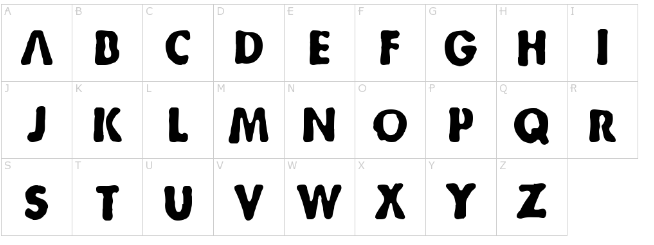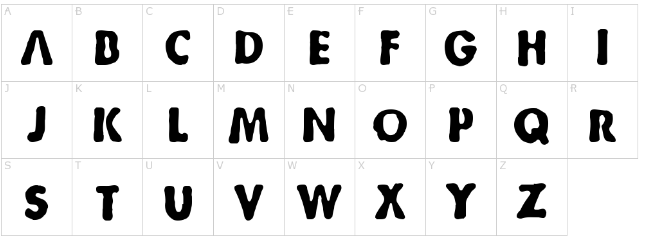
Bộ Font: Font Bootleg
Phân loại: Cá tính
Font Bootleg là một kiểu chữ độc đáo mang đậm phong cách cổ điển và retro, thường được sử dụng trong các thiết kế cần sự phá cách và nghệ thuật. Kiểu chữ này thường có những đặc điểm nổi bật như đường nét thô, không đồng đều, gợi lên cảm giác thủ công và cá tính mạnh mẽ. Bootleg thuộc font chữ design là sự lựa chọn lý tưởng cho các dự án thiết kế như poster phim, bìa album, hoặc các ấn phẩm cần tạo ấn tượng mạnh với người xem. Nếu bạn muốn mang lại cảm giác hoài cổ nhưng vẫn đầy sáng tạo, Font Bootleg sẽ là một lựa chọn tuyệt vời.